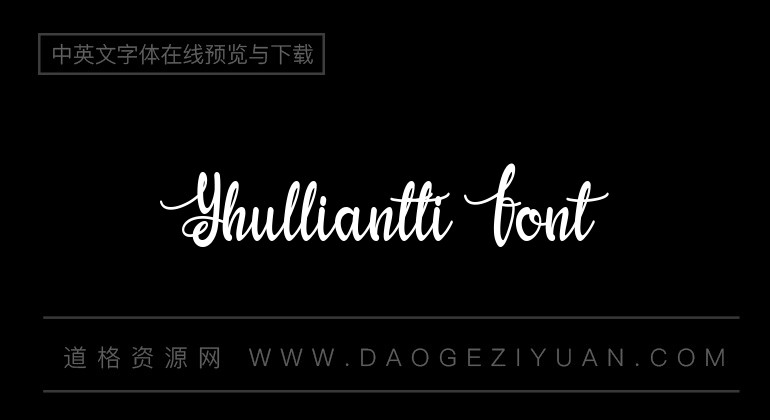
Yhulliantti Font 是一种免费的拉丁字母风格字体,它是由设计师João Paulo Angelim于2016年创建的。该字体具有独特的装饰性,其字母形状的设计灵感来源于人类骨骼结构。 Yhulliantti Font 字体具有多种字重和变体,包括正常、斜体、加粗和加粗斜体,可以满足各种设计需求。此外,该字体还提供了许多特殊字符和标点符号,使其成为一种多功能字体,适用于各种领域,包括广告、品牌设计、海报、标题和标志等。 总的来说,Yhulliantti Font 字体是一种免费的具有装饰性的字体,具有多种字重和变体,适用于各种领域的设计需求。内容介绍
Yhulliantti Font是一款非常不错的手写艺术字体,具有很好的视觉感,适合于文化类的宣传设计、商业类品牌的广告和产品包装设计以及个性化文字排版等较多场景。